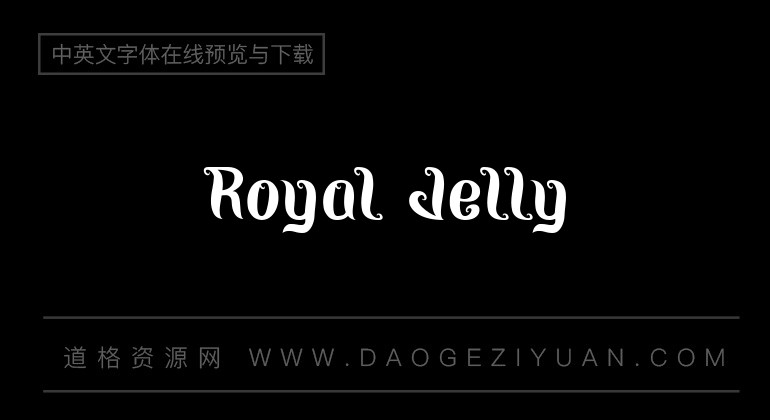
Royal Jelly
Royal Jelly 是一款设计师马克·罗宾斯(Mark Robinson)为墨尔本设计工作室领头羊设计的字体。它是一种脆弱的、古典的、友好的手写字体,具有华丽的自然质感,可用于广泛的设计项目。它拥有丰富的字形,可以满足多种不同的设计需求,包括标题、标签、标语和插图等。它的设计和可读性都非常出色,可以使你的设计更加精致美观。
Royal Jelly是一款非常不错的手写艺术字体,具有很好的视觉感,适合于文化类的宣传设计、商业类品牌的广告和产品包装设计以及个性化文字排版等较多场景。